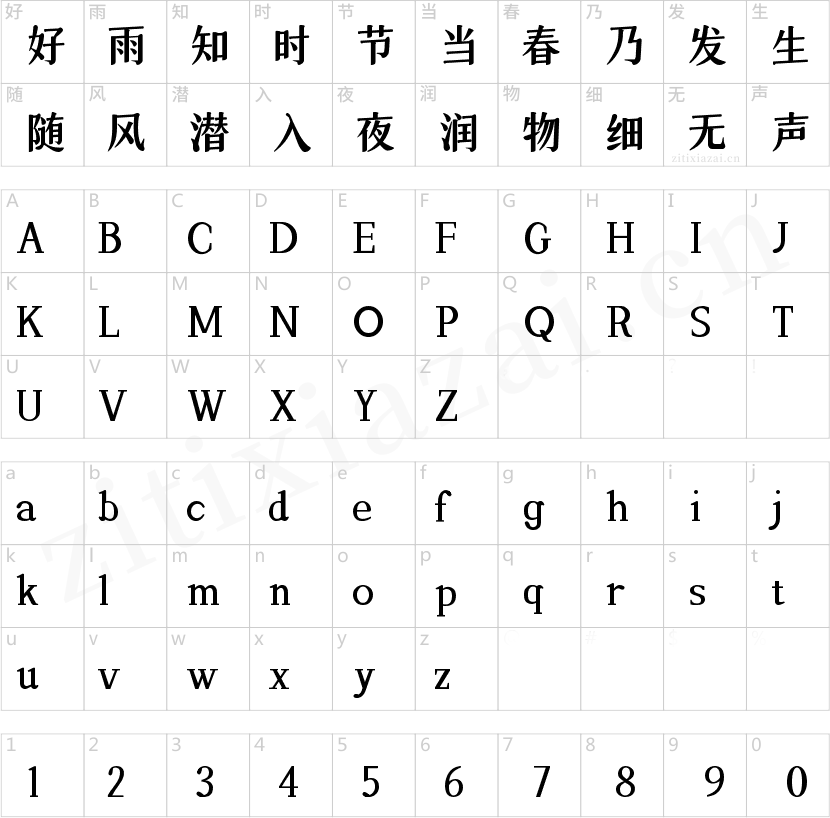
字魂樱花少女体
字魂樱花少女体,这款字体结构工整、笔画清晰,兼顾美观与易读性,适用于标题、正文、海报、包装、LOGO 等多种场景。字形优雅稳定,风格百搭耐看,适配日常排版与创意设计,让文字呈现更舒适、更具质感。字魂樱花少女体一笔一画,皆是细节,以均衡的比例、流畅的线条打造舒适视觉体验,字形端正大气,风格简约现代。无论是商业设计、品牌宣传还是日常排版,都能轻松驾驭,让文字更有格调与力量。字魂樱花少女体字体下载。
字体说明:樱花少女是动图宇宙旗下自有知名IP, 由HelloKitty原作者清水优子的同门师妹水落彩加创作,作者根据自己与 姐姐们的真实故事为灵感改编创作, 塑造了三个时尚爱美的女生形象,三姐妹性格特点各不相同, 因家里院子有一棵大樱花树而得名樱花少女, 同时有“全网第一少女IP”的美誉。